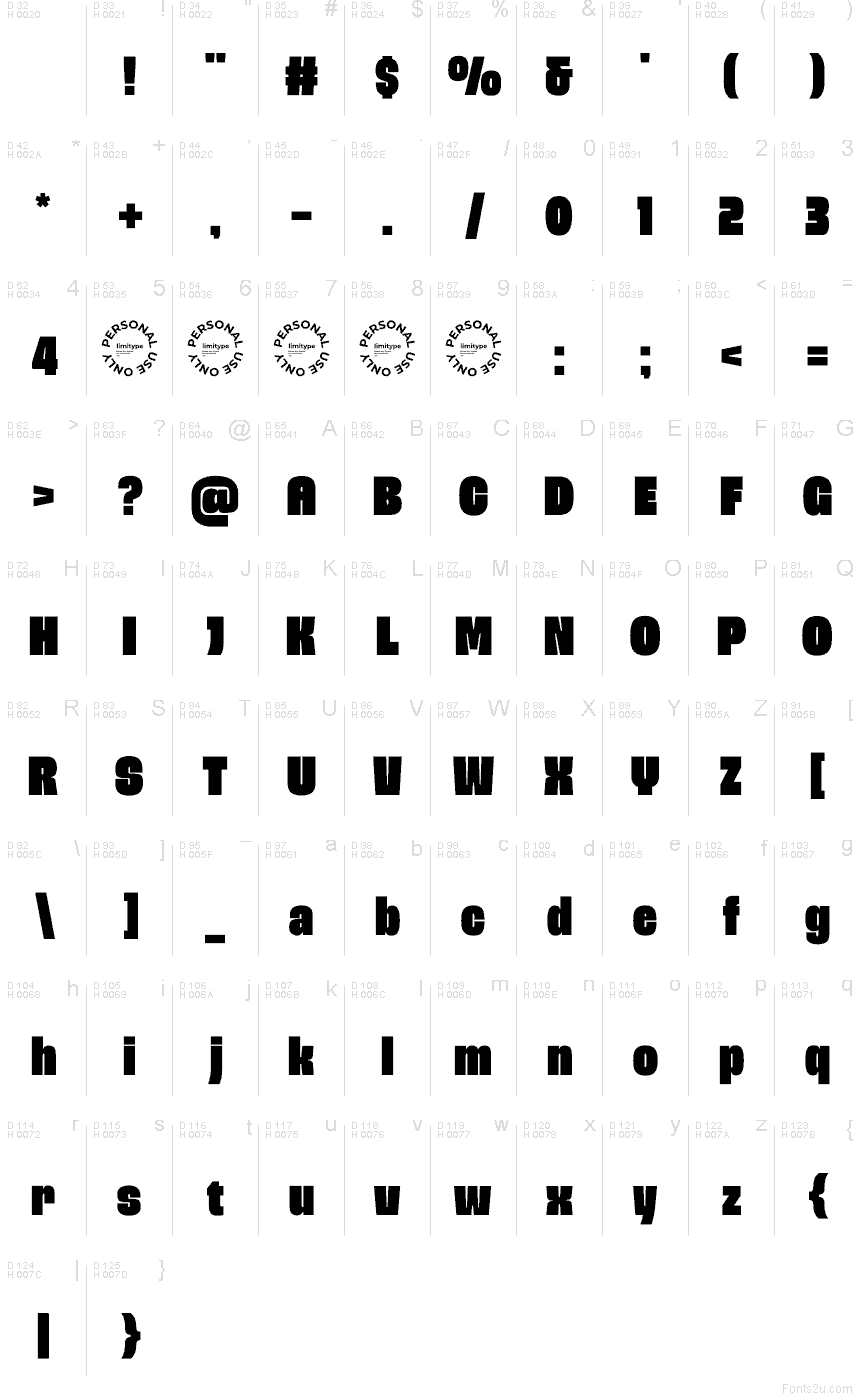
Chuner Demo
Chuner od Limitype je bezplatné ultra-tučné bezpatkové písmo s drsným, plakátovým charakterem. Písmena jsou vměstnána do hustých, zaoblených bloků s podsaditými křivkami a úzkými průhledy, což fontu dodává spíše rázný a kompaktní rytmus než uhlazený moderní vzhled.
Přirozeně zapadne na hudební plakáty, streetwearové grafiky, letáky na akce, obálky či titulky, kde pár slov potřebuje skutečnou váhu. Jako bezplatný font dává smysl i pro ziny a grafiku na sociální sítě, zejména pokud hledáte krátké nadpisy nebo iniciály připomínající monogramy, které působí hutně a bezprostředně.